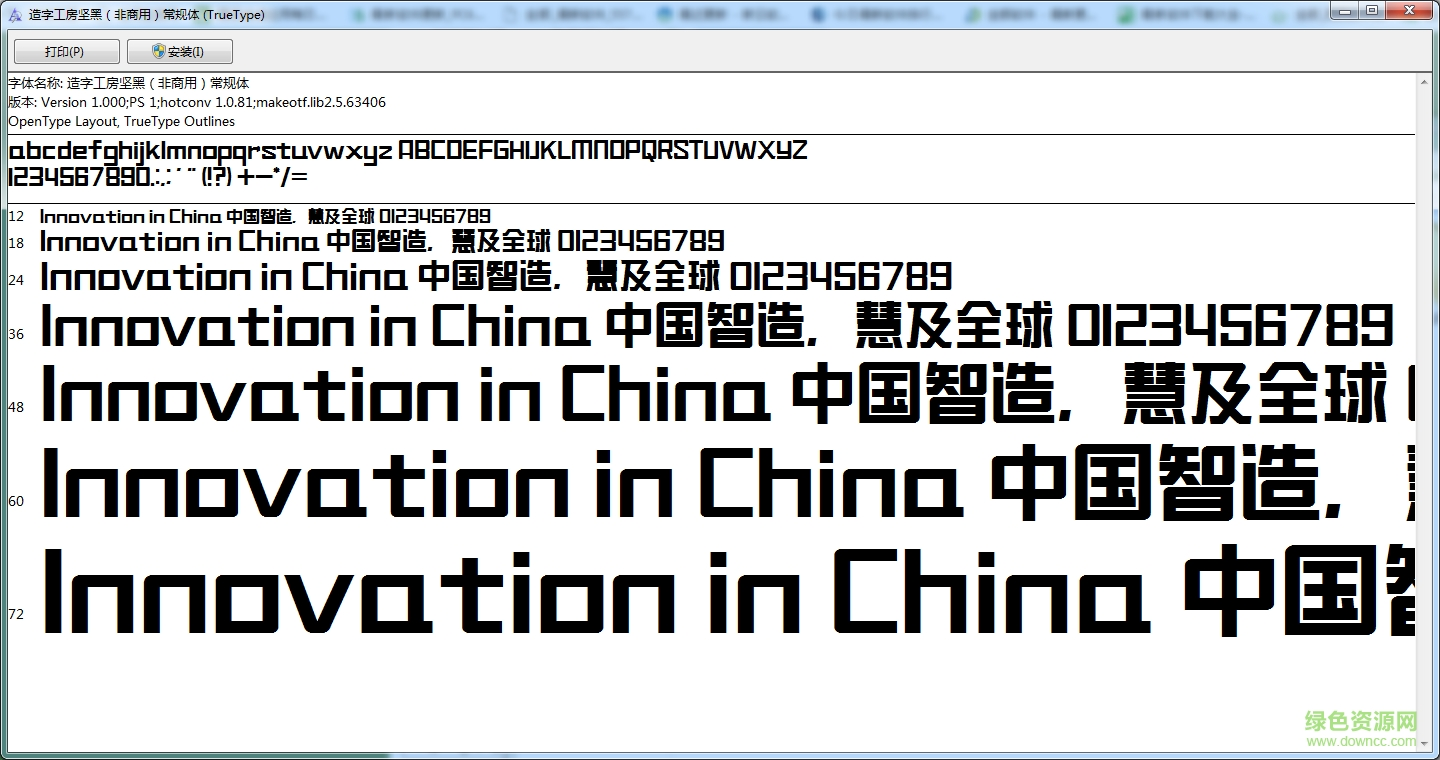
mfjianhei 字體
mfjianhei_nonmmercial regular字體就是造字工房堅(jiān)黑體,該字體邊角圓潤不鋒利,比起一般的黑體多了一點(diǎn)情切感,可以用于藝術(shù)品的宣傳設(shè)計(jì),綠色資源網(wǎng)還有更多免費(fèi)黑體字體供你下載體驗(yàn)!
mfjianhei字體特點(diǎn)
1.結(jié)構(gòu)端正、字形飽滿、筆畫勻稱;
3.字形整體風(fēng)格剛勁有力而不失俊儒之風(fēng),其筆畫中蘊(yùn)含古樸沉厚端凝之勢;
4.在主副標(biāo)題與品牌宣傳上有很大的應(yīng)用空間!
mfjianhei 字體